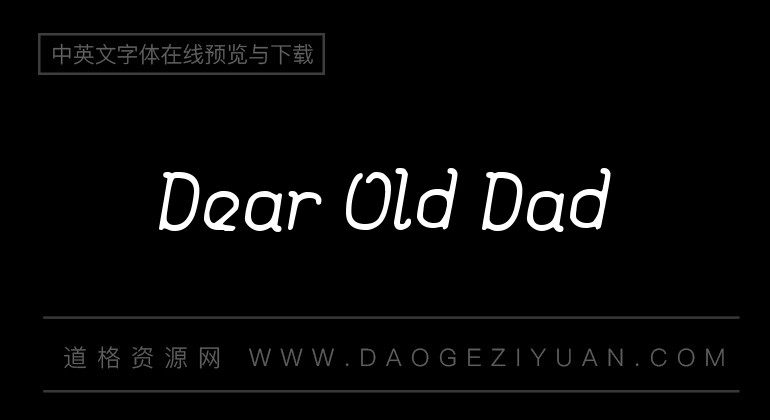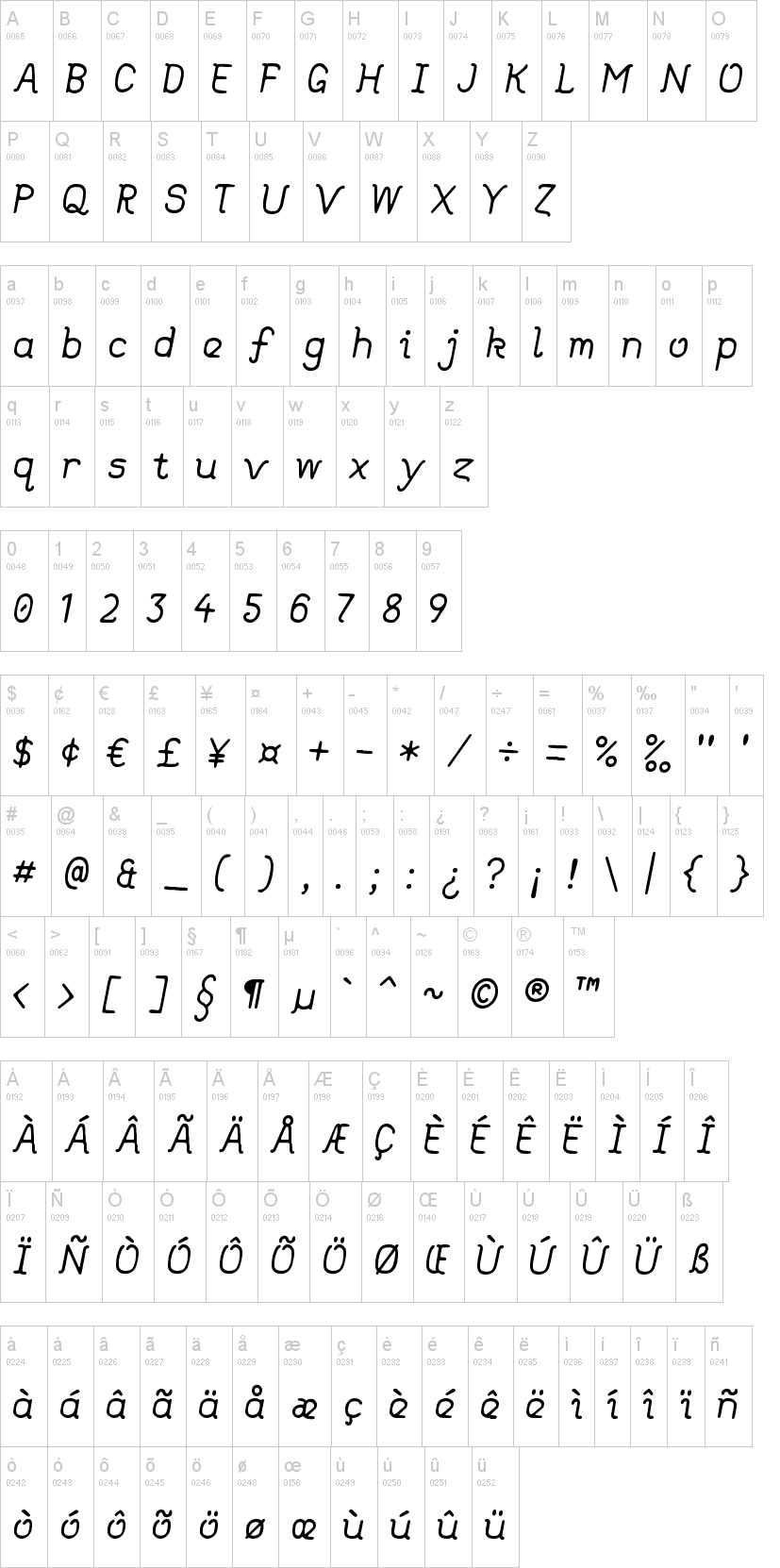
Dear Old Dad
Dear Old Dad 字体是一款基于古老的美国字体的改版,它拥有温暖、友好、温柔、轻松、精致的气息。它具有浓郁的历史气息,能够让您的文字充满温暖和情感。这种字体可以用于创作多种商业用途,如宣传单、海报、标志、标签、书籍封面等。它的设计简单,比较容易看懂,使用起来也很方便。
Dear Old Dad是一款非常不错的手写艺术字体,具有很好的视觉感,适合于文化类的宣传设计、商业类品牌的广告和产品包装设计以及个性化文字排版等较多场景。